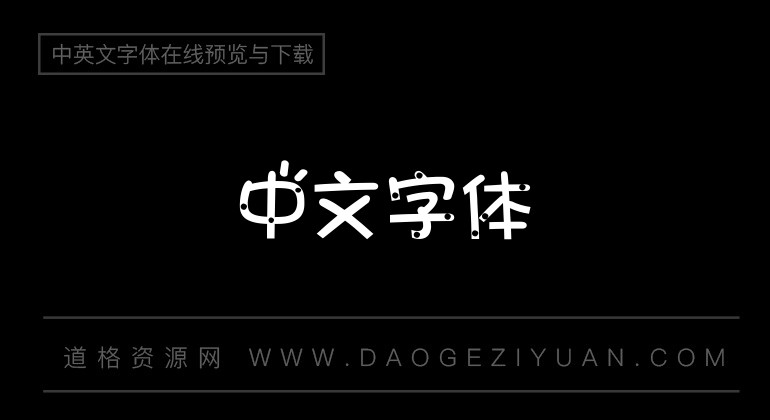
萝莉体 第二版
萝莉体 第二版 字体是一款由日本设计师柳田英雄设计的欧美风格字体,它以柔美的线条呈现出温柔可爱的萝莉感,是一款适合提升萌系文字效果的字体。萝莉体 第二版 字体的特点是在英文字母的设计中,采用了椭圆形的线条,使字体看起来更加柔美,而在数字设计上,则采用了更加细腻的线条,使数字的视觉效果更加柔美,从而营造出一种可爱的萝莉感。
萝莉体 第二版是一款非常不错的手写艺术字体,具有很好的视觉感,适合于文化类的宣传设计、商业类品牌的广告和产品包装设计以及个性化文字排版等较多场景。